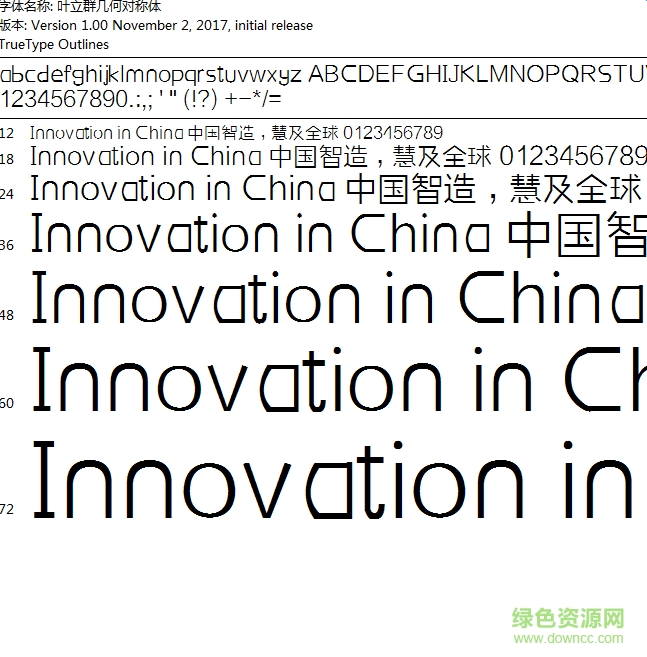
葉立群幾何對(duì)稱體是葉立群字庫中很實(shí)用的一款簡體字體,這款字體寫出來的字是很好看的,規(guī)范整齊,而且可以用于很多方面,歡迎有需要的朋友來綠色資源網(wǎng)下載。
葉立群幾何對(duì)稱體字體是一款很不錯(cuò)的電腦字體,可以用于書本印刷、廣告設(shè)計(jì)等方面,喜歡的朋友可以來綠色資源網(wǎng)下載。